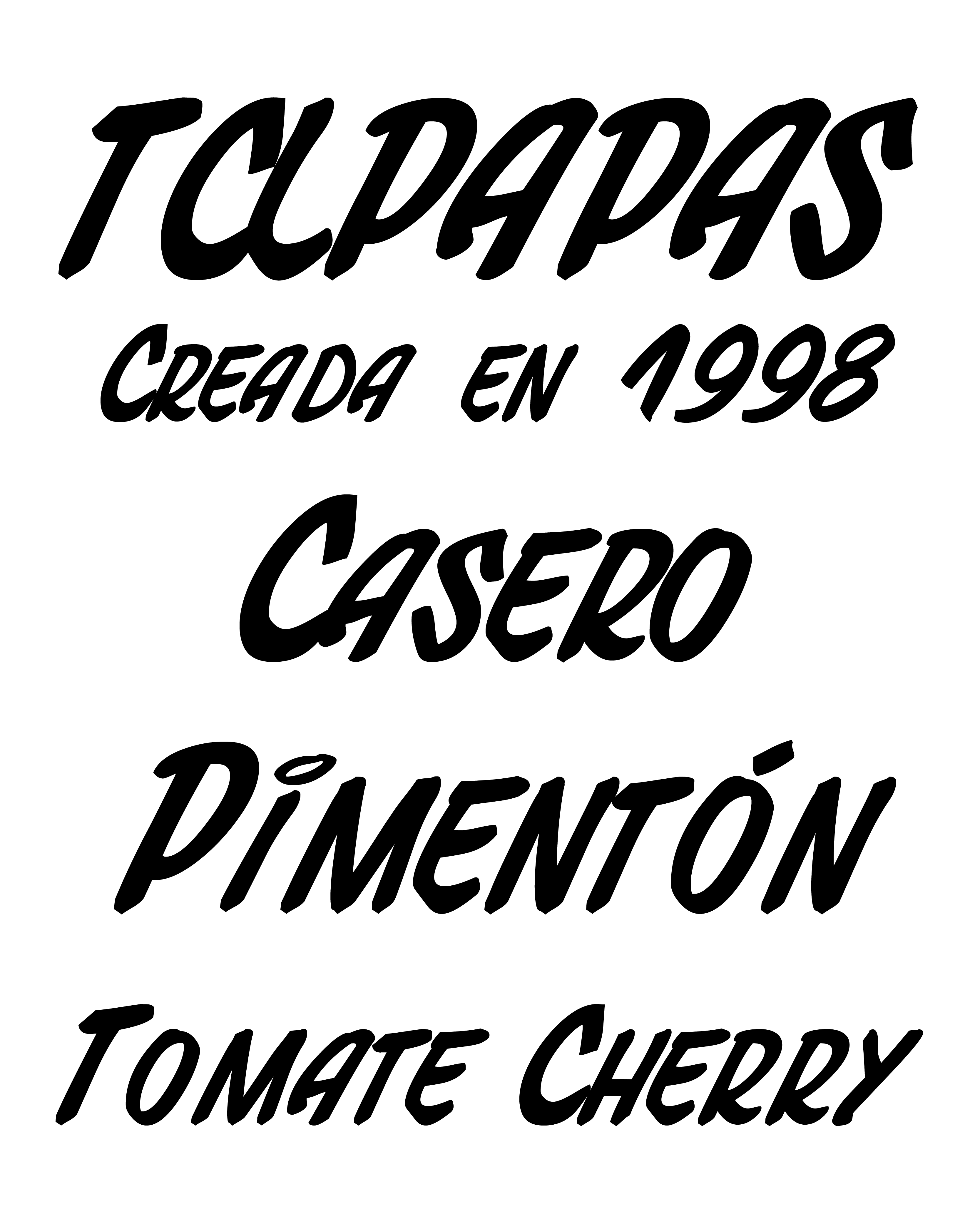
TCLpapas Regular
| Año | 1998 |
| Créditos | José Soto, Luis Antonio Rojas |
| Descripción | Papas es parte de la colección del proyecto “Tipografías Urbano—Populares”, cuyo objetivo es rescatar rótulos vernáculos de diferentes contextos. El uso de este tipo de letra está muy extendido en entornos comerciales e informativos en el espacio público. |
| Estudio | TUPs |